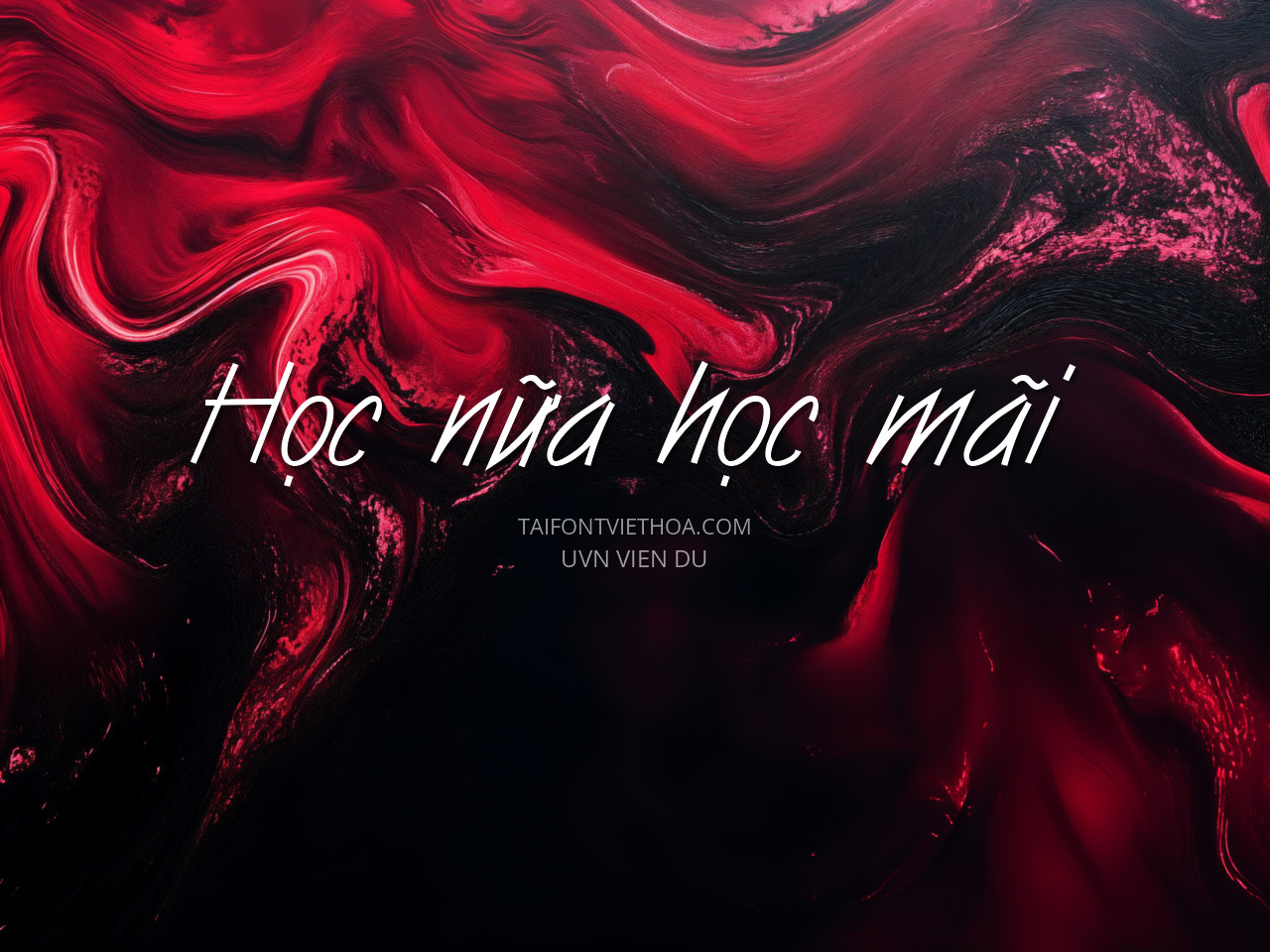
Font việt hóa UVN Vien Du
Giới thiệu về font UVN Vien Du
UVN Vien Du là một font chữ mang phong cách nhẹ nhàng, bay bổng và gợi mở sự hoài niệm như một chuyến viễn du qua không gian ký ức. Với hình ảnh ẩn dụ từ chính tên gọi, font mang đến cảm giác thư thái, mộng mơ và có phần lãng mạn – lý tưởng để sử dụng trong các thiết kế mang tính cá nhân, tâm trạng hoặc nghệ thuật sáng tạo. Font được sưu tầm và chia sẻ bởi thành viên Font Chuẩn, và đã được taifontviethoa.com chọn lọc kỹ lưỡng để ứng dụng trong các dự án mang sắc thái tình cảm, văn hóa và truyền thống Việt.
Đặc điểm thiết kế và ứng dụng của UVN Vien Du
Font UVN Vien Du sở hữu cấu trúc thanh mảnh, các đường cong mềm mại và tỷ lệ chữ mang tính đối xứng vừa đủ, tạo cảm giác bay nhẹ và tinh tế. Đường nét có độ tương phản thấp, giúp mắt nhìn dễ chịu và phù hợp với các thiết kế thiên về cảm xúc, nghệ thuật hoặc nội dung nhẹ nhàng. Font hỗ trợ tiếng Việt đầy đủ, đảm bảo hiệu suất hiển thị tốt trên cả bản in lẫn môi trường kỹ thuật số.
Ứng dụng lý tưởng: bìa sách văn học, nhật ký, blog tâm sự, thiệp chúc mừng, ấn phẩm sự kiện cá nhân hoặc nghệ thuật. Ngành nghề phù hợp: sáng tạo nội dung, thiết kế cảm xúc, văn hóa nghệ thuật, giáo dục nhân văn và truyền thông cộng đồng.